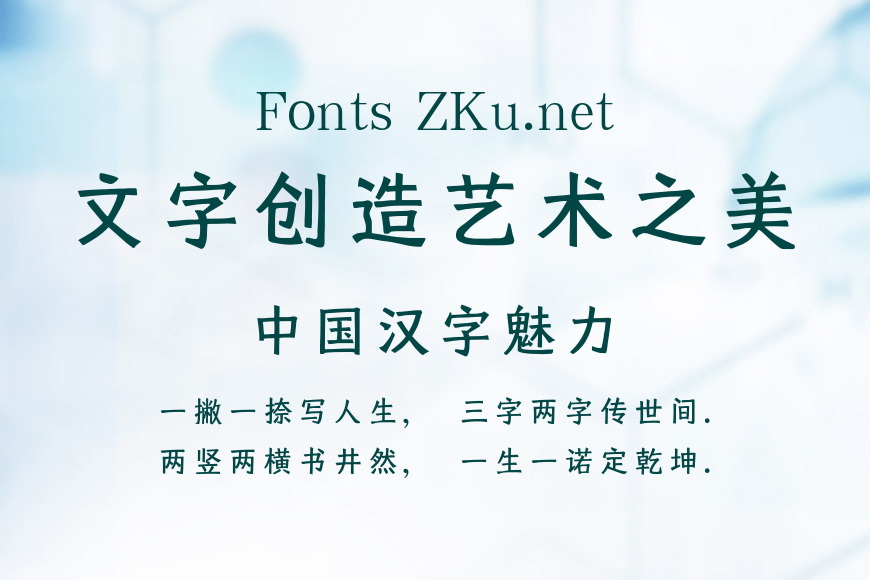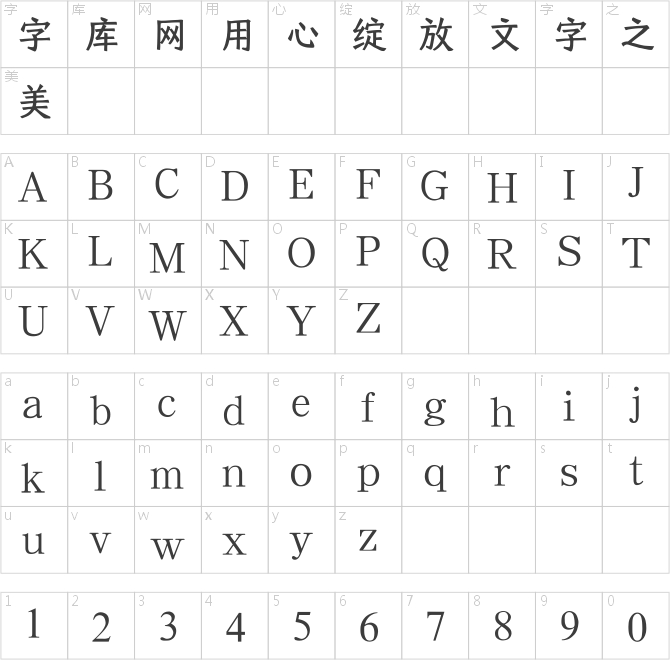
字体名称: 懒设计字由公益
作者版权: 懒设计/字由
懒设计字由公益体
懒设计字由公益体是由在线设计神器懒设计与让设计更有价值的字由联合推出的一款免费商用公益字体
懒设计字由公益体字体字库是一款让人赏心悦目、百看不厌的中文字体,适合各类广告和产品包装设计应用,字体大小7.29MB,格式为ttf字体,上传用户是云泥,作者/版权方为懒设计/字由